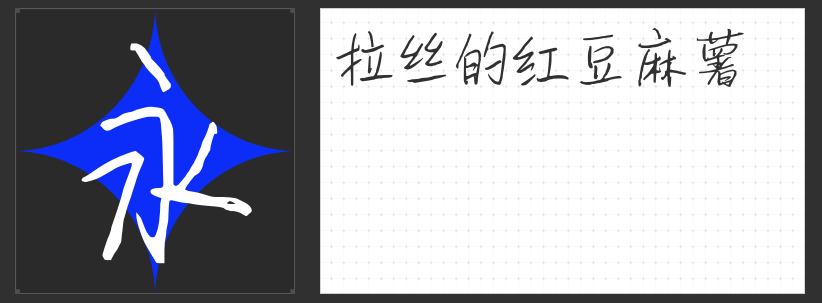
四款手写字体推荐:让设计跃动自然灵韵
手写字体的独特魅力在于其“不完美中的温度”,一笔一划间传递着书写者的情绪与个性。在品牌视觉、社交媒体、视频包装等场景中,手写字体能快速打破刻板印象,拉近与受众的情感距离。本文精选四款风格迥异的手写字体,涵盖童趣天真、谐趣活泼、文艺写意与灵动清新四大方向,助力设计师解锁创意新可能。
一、小豆岛默陌乐童简
“童心是比野心更难得的梦想”——这款字体以儿童手写为灵感,采用“上松下紧”的错落结构,笔画宽细一致、转折圆润,仿佛孩童握笔时用力不均的“笨拙感”。字间距松散却充满呼吸感,尤其适合母婴产品包装、儿童绘本封面或教育类海报设计。其无衬线化的处理弱化了传统书法的仪式感,更贴近现代亲子场景的轻松氛围。设计师可自由调整字符间距或叠加涂鸦元素,创造专属童趣风格。
二、小豆岛惠中谐趣简繁
若需为二次元动画字幕、旅行vlog标题或鬼畜视频增添“无厘头”幽默感,这款结构整体倾斜15°的字体堪称不二之选。它通过解构正统书法笔画,将横竖撇捺转化为“摇摆不定的曲线”,制造出重心偏移的动态错觉。
三、小豆岛默陌秀丽简
以传统书法为根基,这款字体通过“疏可走马,密不透风”的布局哲学,将点划的随机性与节奏感发挥到极致。笔锋时而如枯笔扫过宣纸,时而如浓墨滴落晕染,粗细对比强烈却不显突兀。适用于茶饮品牌包装、国风文创海报或诗歌集封面设计,能瞬间提升作品的文化厚重感。
四、MyFont自由简 细体
这款字体以“极简主义”为核心理念,笔画纤细如丝却富有弹性,转折处采用圆角处理,整体呈现“飘逸而不失力度”的视觉效果。其0.8:1的宽高比优化了小字号下的可读性,尤其适合社交媒体配图、产品说明文档或女性向品牌LOGO。
从孩童的涂鸦到书法的写意,从谐趣的倾斜到灵动的纤细,这四款手写字体以不同维度诠释了“人为笔触”的感染力。设计师可根据项目调性自由搭配,让每一处文字都成为传递情绪的“视觉音符”。